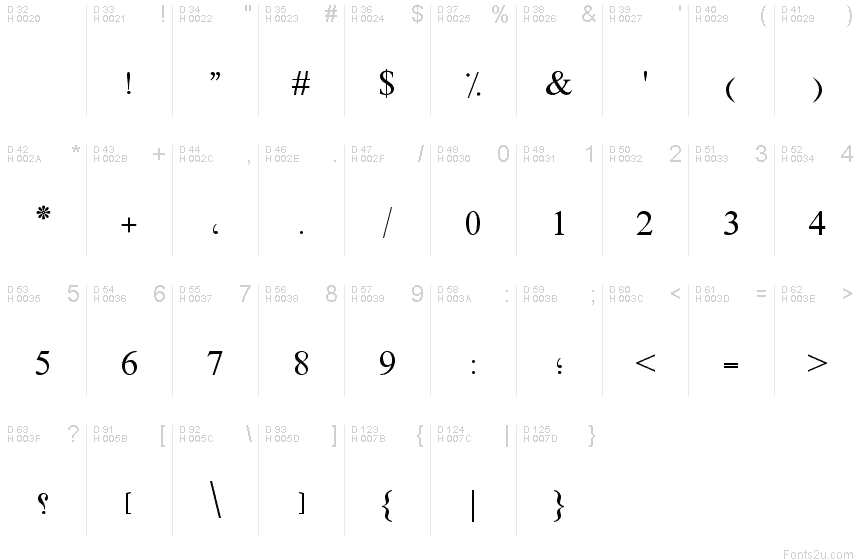
UL Noreen Bold di Urdulife è un carattere arabo display gratuito dal ritmo calligrafico compatto. Le lettere appaiono dense ed enfatiche, con tratti spessi e fluidi, curve arrotondate e terminali decisi che conferiscono alla riga un vivace tocco calligrafico, ben lontano dalla rigidità geometrica.
Si adatta perfettamente a manifesti culturali, copertine di libri, intestazioni devozionali, volantini per eventi e packaging, laddove una linea araba audace richieda calore e presenza. Essendo un font gratuito, è ideale anche per titoli brevi, testate e citazioni in evidenza, grazie alle forme dense e collegate che creano un blocco di testo di grande impatto con il minimo sforzo.